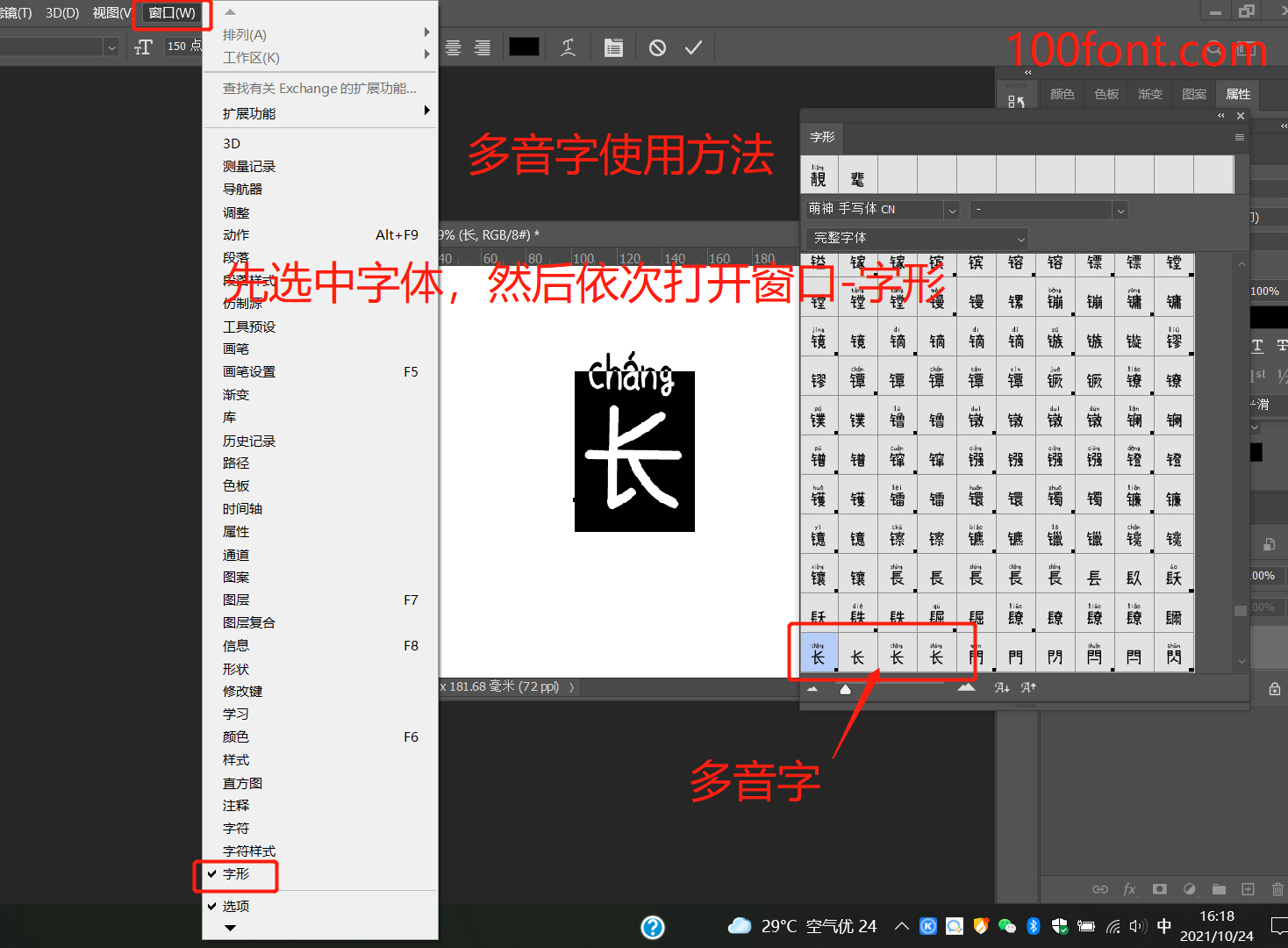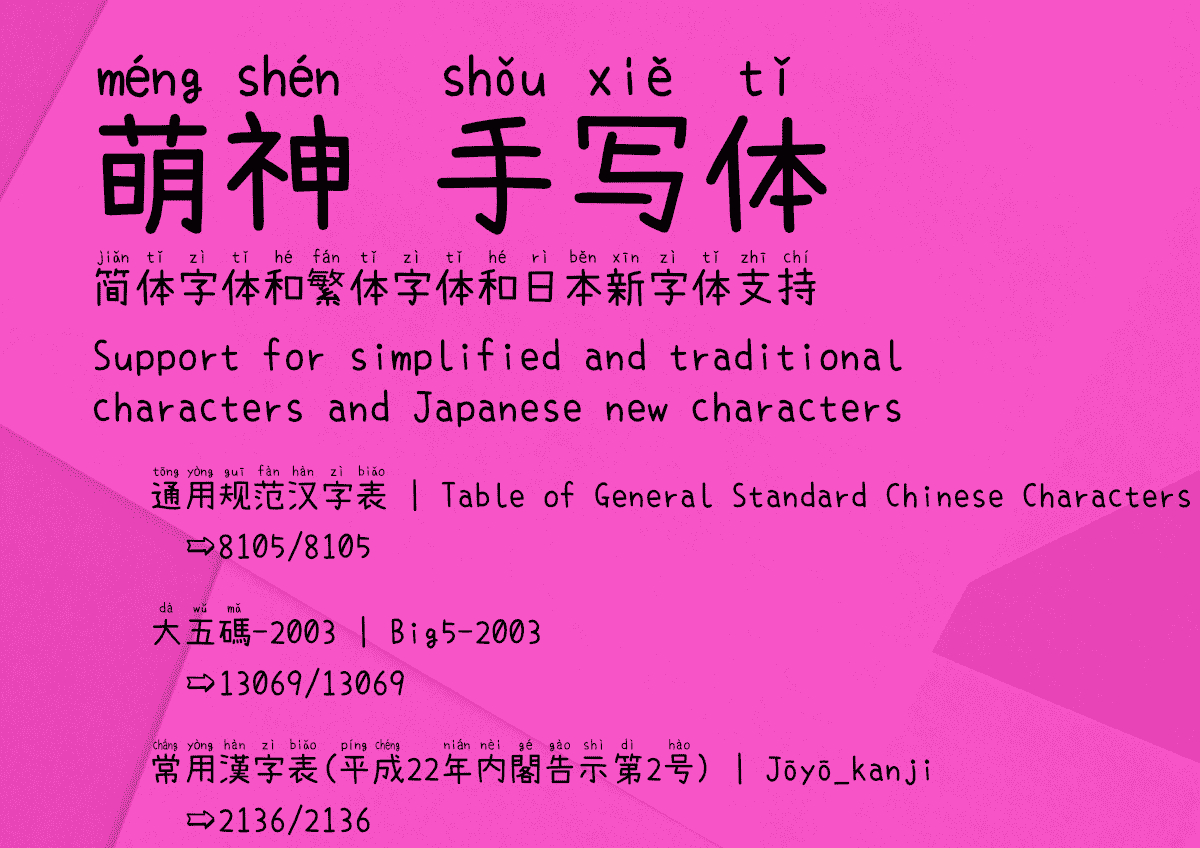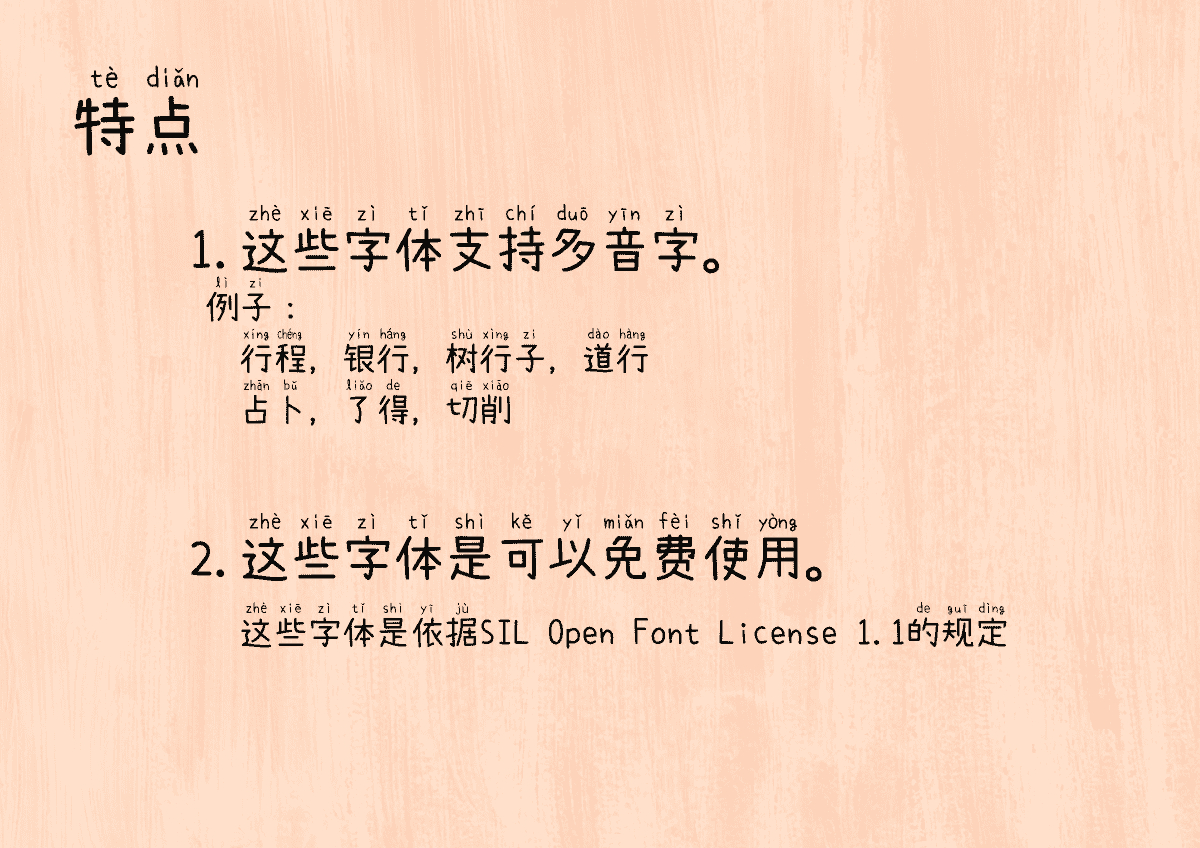
萌神手寫體是由小賴字體進行改造而成的一款免費商用字體,採用SIL Open Font License 1.1授權協議發佈,手寫風格,自帶拼音,支持多音字, 適合用於幫助學生更快地學習和閱讀漢語。基本上是可以顯示日語、簡體字和繁體字的字體,是在簡體字和繁體字中加入拼音的字體的製作。
萌神手寫體實現了上下文替換(feature of“rclt”at GSUB)以支持多音字。另外,還可以使用Unicode IVS(表意文字變體選擇器)來切換到不同的拼音。